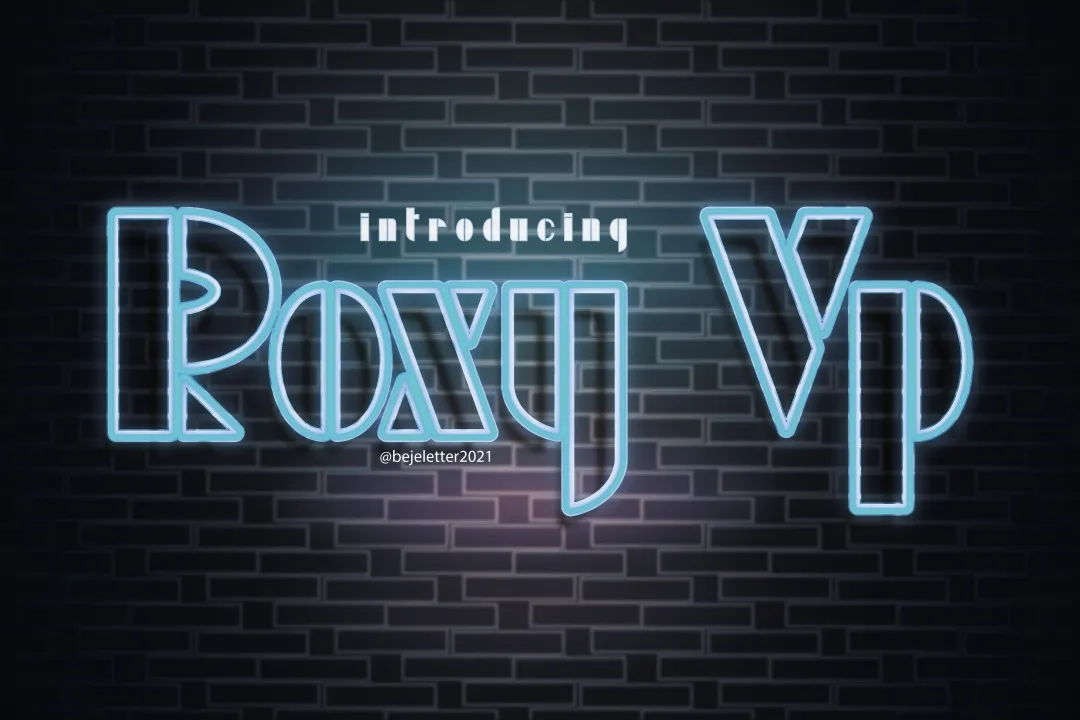
Esta é uma fonte tipo Display, projetada por designers para quem aprecia um olhar simples e descontraído, com um estilo muito limpo e clean. Suas linhas sóbrias e clara oferecem um aspecto agradável que se destaca em ambientes modernos, esportivos, dedicados à jogos ou automotivos, ou até mesmo em temas futuristas e tecnológicos. Ideal para usar em títulos e textos de display onde você deseja transmitir uma sensação futurista e dinâmica. A fonte Roxy Vp chega a nós com duas versões estilizadas que capturam essa essência: uma que possui linhas claras, e outra que adota um tom mais acinzentado. Ambas as opções são perfeitamente adaptáveis para criar um estilo único e moderno em projetos digitais e impressos, seja para marcas publicitários ou anúncios de tecnologia. Sem dúvida, a font Roxy Vp é uma escolha ideal para quem busca uma aparição futurista e ativa em qualquer projeto visual.